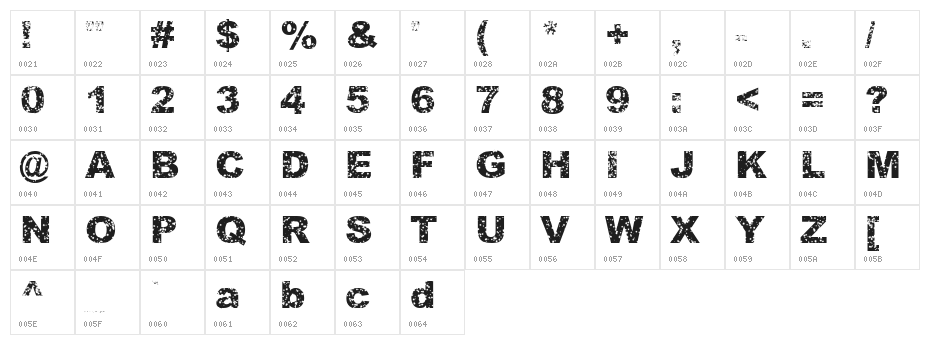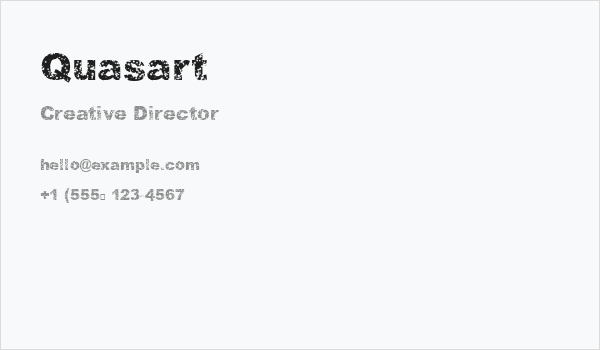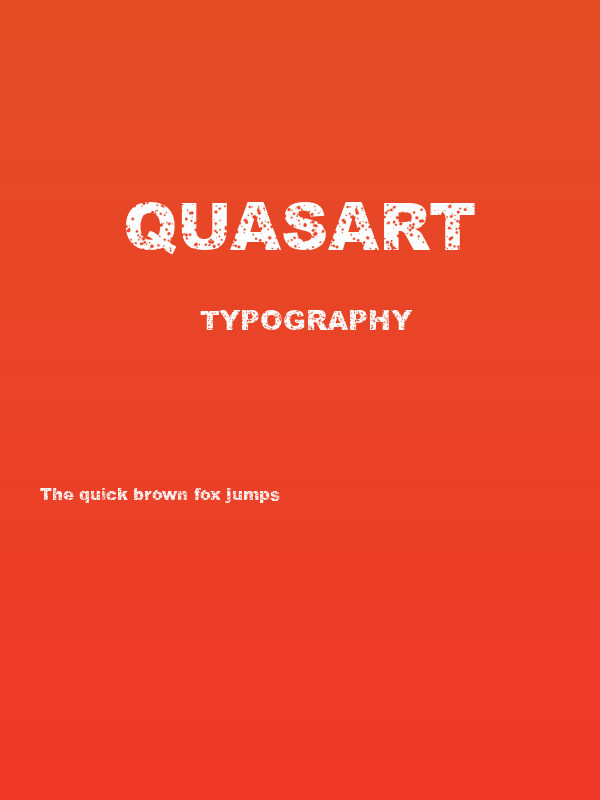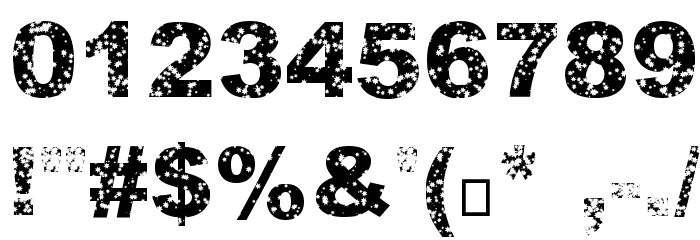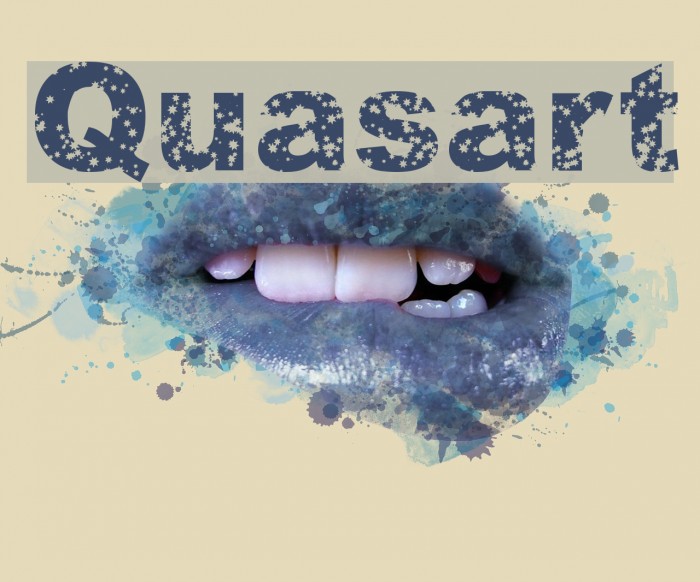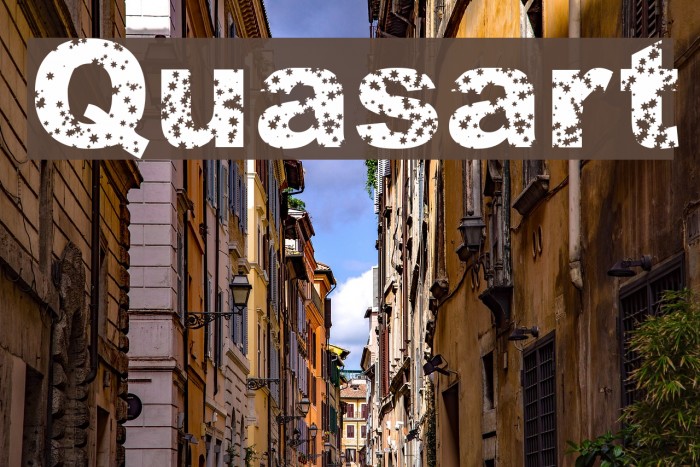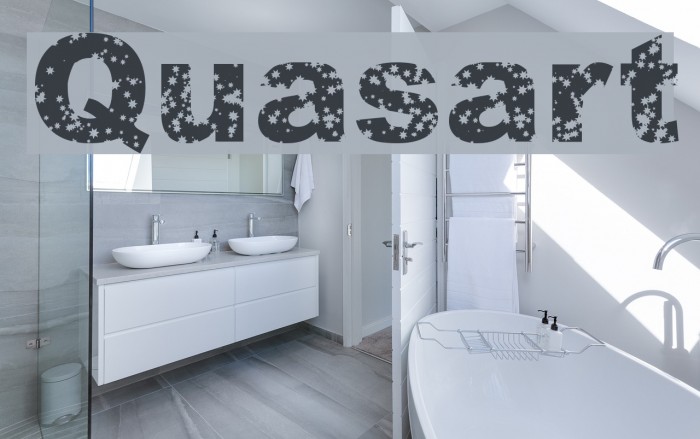
Quasart Font
| Gesamtstil | Vintage |
| Vorgeschlagene Projekte | Ideal for posters, album covers, branding for edgy or alternative products, and any design needing a grunge or industrial vibe. |